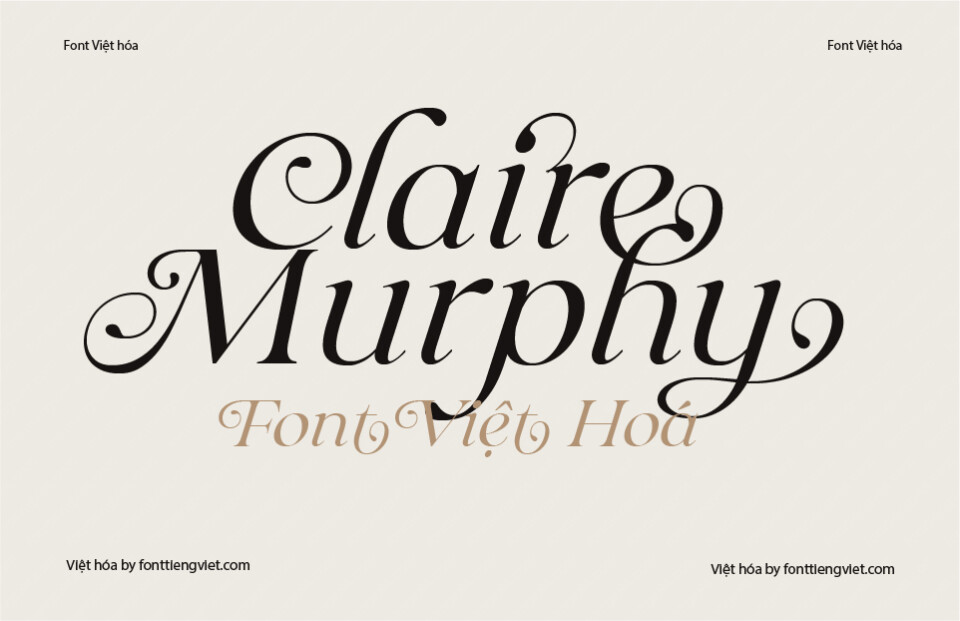
Font Việt hóa 1FTV VIP Claire Murphy
Font Việt hóa 1FTV VIP Claire Murphy – Font chữ sang trọng cho thiết kế hiện đại
Trong thế giới đồ họa hiện nay, việc tìm kiếm một bộ Font Việt hóa 1FTV VIP Claire Murphy chất lượng là điều mà bất kỳ nhà thiết kế nào cũng mong muốn. Đây là một phông chữ mang phong cách hiện đại, thanh lịch và cực kỳ tinh tế, phù hợp cho nhiều mục đích sáng tạo khác nhau từ in ấn đến truyền thông kỹ thuật số. Khi sử dụng Font Miễn Phí này, bạn sẽ nhận thấy sự khác biệt rõ rệt trong cách trình bày nội dung, giúp thông điệp truyền tải trở nên chuyên nghiệp và thu hút hơn đối với người xem. Đặc biệt, phiên bản Việt hóa này đã được tối ưu hóa hoàn toàn để hiển thị các ký tự có dấu một cách chuẩn xác, không bị lỗi font khi gõ tiếng Việt trên các phần mềm thiết kế phổ biến hiện nay.
Đặc điểm nổi bật của Font Việt hóa 1FTV VIP Claire Murphy
Phong cách thiết kế tinh xảo và ứng dụng cao
Bộ Font Việt hóa 1FTV VIP Claire Murphy nổi tiếng với những đường nét thanh mảnh nhưng vẫn giữ được sự chắc chắn và cân đối. Kiểu chữ này thuộc nhóm Serif (có chân) hiện đại, mang lại cảm giác cổ điển hòa quyện cùng hơi thở thời đại mới. Các nhà thiết kế thường ưu tiên lựa chọn bộ font này cho các dự án yêu cầu tính thẩm mỹ cao như thiết kế logo thương hiệu cao cấp, thiệp mời đám cưới, bìa tạp chí thời trang hay các ấn phẩm quảng cáo cho ngành làm đẹp. Sự mềm mại trong từng nét chữ giúp tạo nên một không gian thiết kế thoáng đãng và sang trọng, dễ dàng gây ấn tượng mạnh mẽ với khách hàng ngay từ cái nhìn đầu tiên.
Khả năng tương thích và tối ưu hóa tiếng Việt
Một trong những ưu điểm lớn nhất của Font Việt hóa 1FTV VIP Claire Murphy chính là bộ dấu được chăm chút tỉ mỉ. Việc Việt hóa không chỉ đơn thuần là thêm dấu mà còn là sự căn chỉnh sao cho các dấu thanh như huyền, sắc, hỏi, ngã, nặng hòa hợp hoàn hảo với cấu trúc của chữ cái gốc. Điều này giúp văn bản tiếng Việt trông tự nhiên, không bị rời rạc hay mất cân đối như các bản font chưa được tối ưu. Nhờ đó, các bạn học sinh, sinh viên hay giáo viên có thể dễ dàng sử dụng phông chữ này để làm bài thuyết trình, báo cáo hoặc tài liệu giảng dạy sinh động hơn.
Cách sử dụng Font Việt hóa 1FTV VIP Claire Murphy hiệu quả
Kết hợp font chữ trong bố cục thiết kế
Để tận dụng tối đa vẻ đẹp của Font Việt hóa 1FTV VIP Claire Murphy, bạn nên kết hợp nó với các font chữ không chân (Sans-serif) đơn giản cho phần nội dung văn bản dài. Sự đối lập giữa nét chữ có chân điệu đà của Claire Murphy ở phần tiêu đề và sự gọn gàng của font không chân ở phần thân bài sẽ tạo nên một hệ thống phân cấp thị giác rõ ràng. Đừng quên chú ý đến khoảng cách giữa các chữ cái (kerning) và khoảng cách dòng (leading) để đảm bảo văn bản luôn dễ đọc và duy trì được sự tinh tế vốn có của bộ phông chữ này trên mọi chất liệu hiển thị.
Lưu ý khi lựa chọn màu sắc và bối cảnh
Màu sắc đóng vai trò quan trọng khi sử dụng Font Việt hóa 1FTV VIP Claire Murphy. Những gam màu trung tính như đen, trắng, vàng gold hoặc các tông màu pastel sẽ tôn vinh triệt để vẻ quý phái của phông chữ. Trong môi trường học đường, phông chữ này có thể dùng để thiết kế tiêu đề bảng tin hoặc các chứng nhận khen thưởng, giúp tạo cảm giác trang trọng và khích lệ tinh thần cho người nhận. Việc hiểu rõ tính chất của font sẽ giúp bạn biến những ý tưởng đơn giản trở thành những tác phẩm nghệ thuật có giá trị thẩm mỹ cao.
Kết luận về bộ font chữ cao cấp